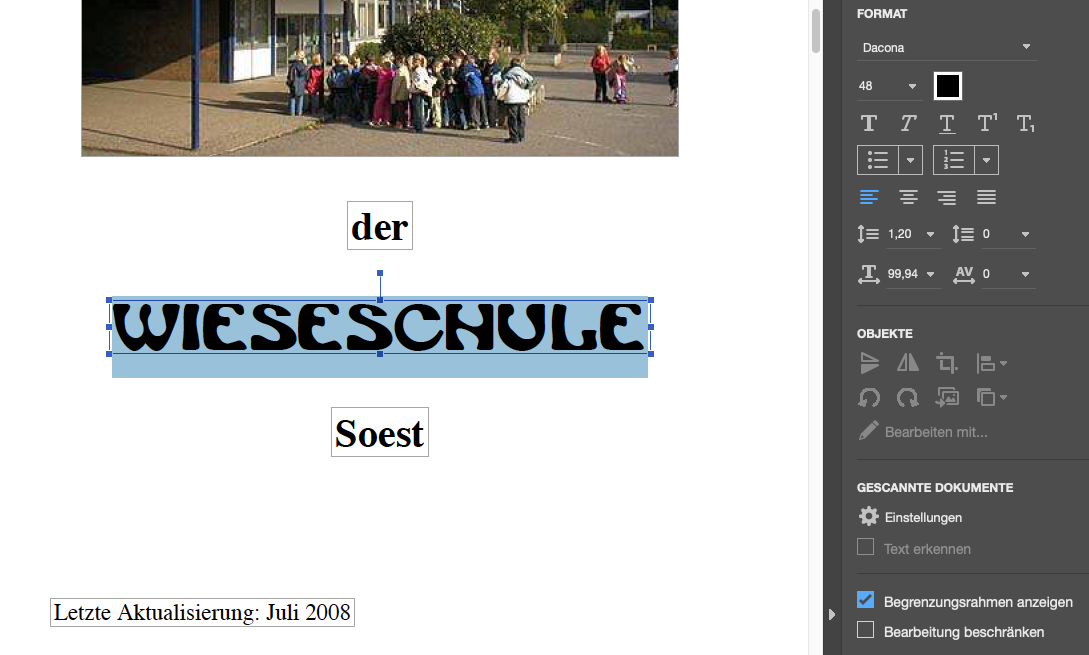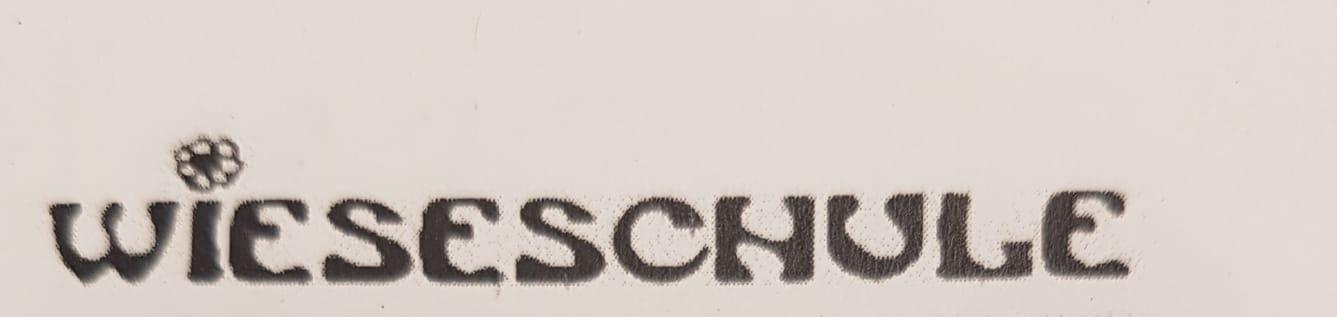
Suche Jugendstilschrift einer Grundschule
ich suche die Schrift im Anhang. Dies ist die Schrift einer Grundschule in Soest.
Leider habe ich sehr wenig Hintergrundinfos. Habe auch keine Hoffnung das jemand dort weiß, wann oder wie die Schrift eingeführt wurde.
Whatthefont liefert leider keine brauchbaren Ergebnisse – wahrscheinlich auch aufgrund der schlechten Vorlage.
Der Name der Schrift wäre natürlich super. Ähnliche Schriften würden mir aber auch schon weiterhelfen.
"Dacona" heißt er.
Ich habe keine vertrauensvolle Quelle gefunden, daher gebe ich keine an.